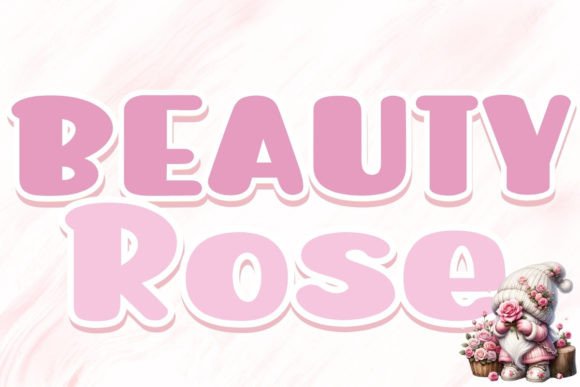
Beauty Rose
適切なデザイン要素を見つけるのは難しい場合がありますが、Beauty Roseは作品を即座に引き立てる優れたコレクションを提供します。
POD(オンデマンド印刷)製品、結婚式の招待状、またはソーシャルメディアのグラフィックを作成している場合でも、Beauty Roseは理想的です。